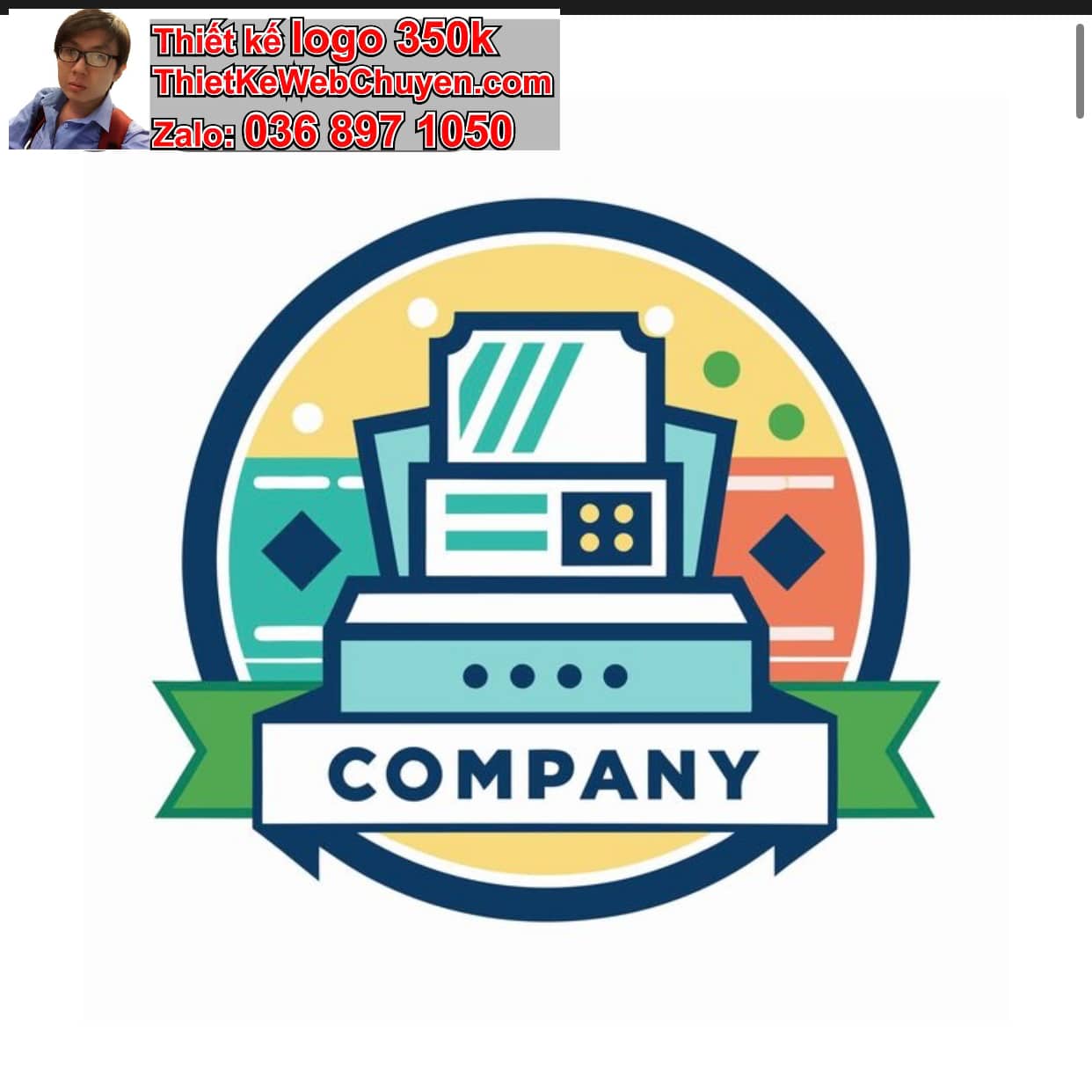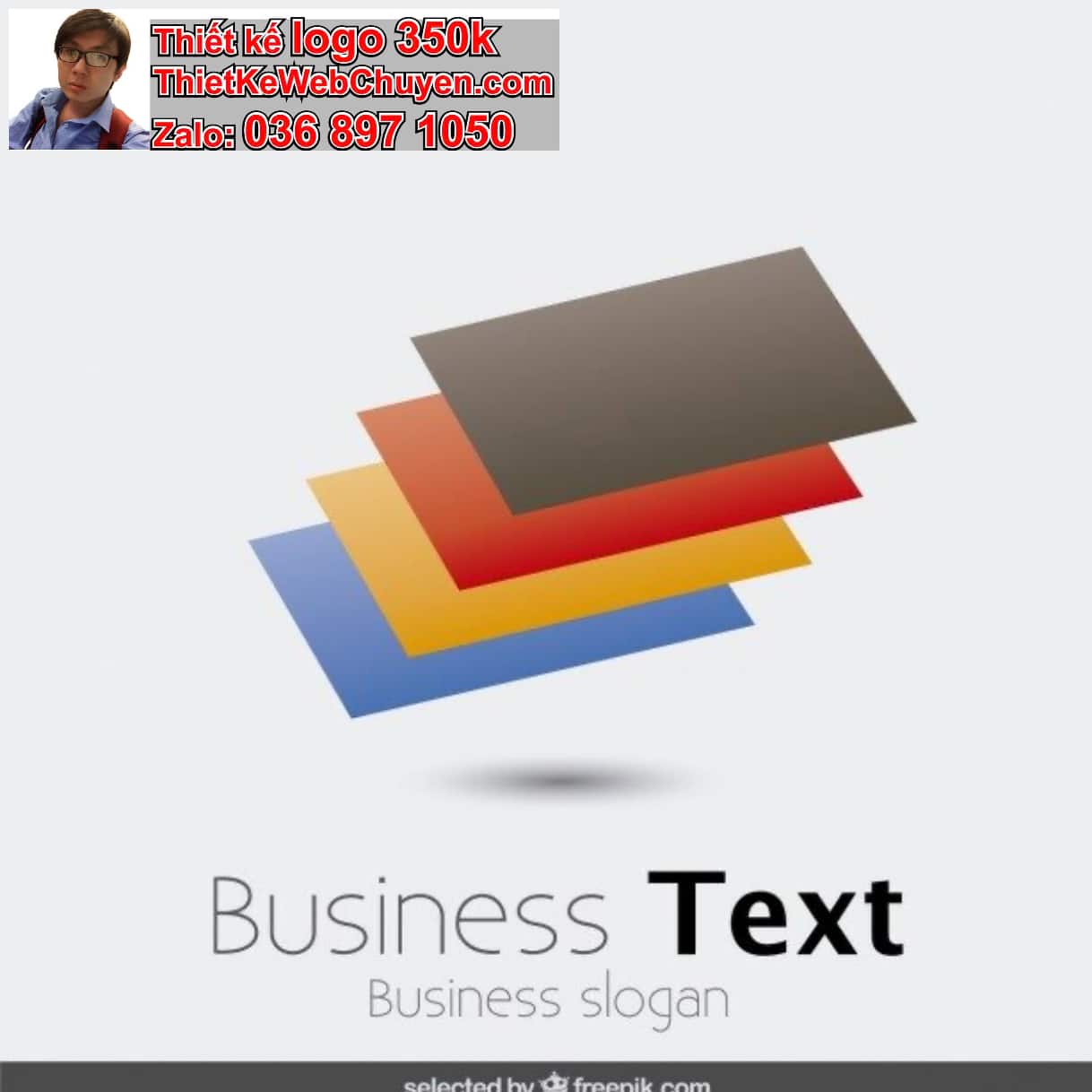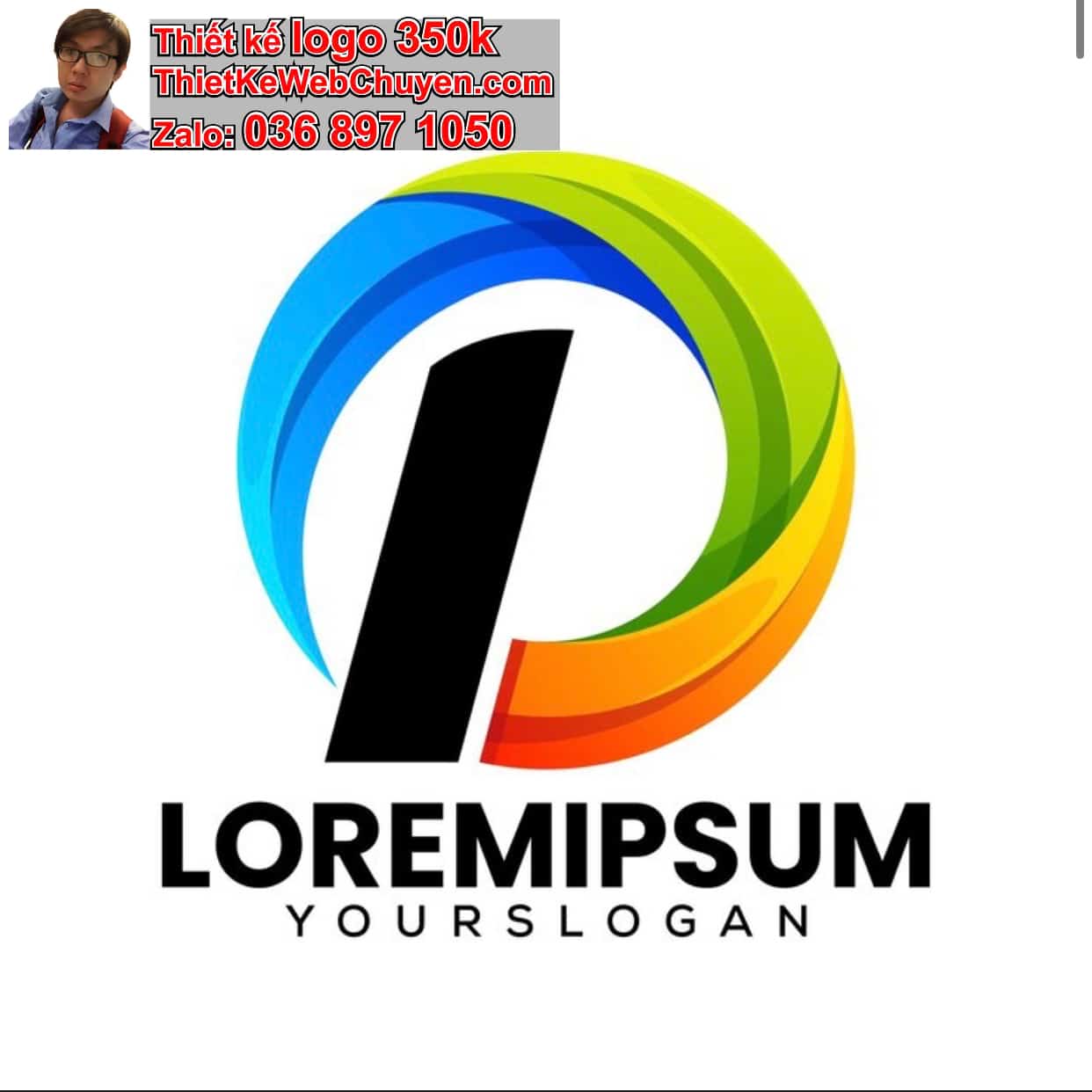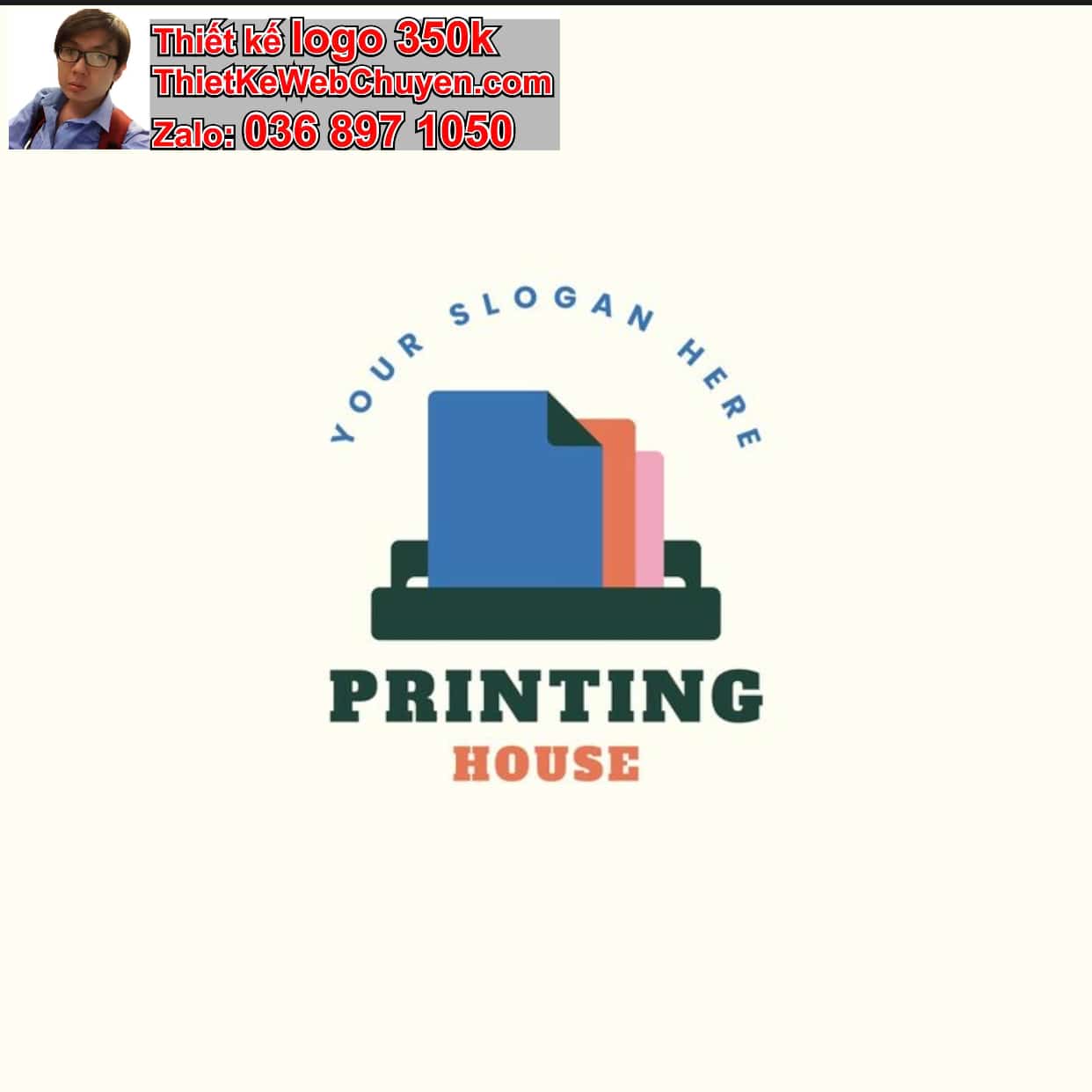
Bài viết này cung cấp hướng dẫn toàn diện về cách logo công ty chọn màu font biểu tượng khi ngân sách thấp, tập trung vào các nguyên tắc thiết kế hiệu quả và công cụ miễn phí. Bạn sẽ khám phá những bí quyết chọn màu sắc, font chữ và biểu tượng để tạo ra một nhận diện thương hiệu chuyên nghiệp mà không vượt quá hạn mức chi tiêu. Đảm bảo rằng dù với ngân sách hạn chế, bạn vẫn có thể sở hữu một logo công ty ấn tượng và thu hút.
Bạn đang khởi nghiệp hay điều hành một doanh nghiệp nhỏ với ngân sách hạn hẹp? Việc tạo dựng một thương hiệu mạnh mẽ bắt đầu từ một logo công ty ấn tượng, nhưng làm thế nào để có được một logo công ty chọn màu font biểu tượng khi ngân sách thấp mà vẫn chuyên nghiệp và hiệu quả? Đây là một thách thức chung mà nhiều chủ doanh nghiệp gặp phải.
Đừng lo lắng! Trong bài viết này, chúng ta sẽ cùng khám phá những chiến lược thông minh, các mẹo thực tế và nguồn tài nguyên hữu ích để giúp bạn tạo ra một logo công ty chọn màu font biểu tượng khi ngân sách thấp nhưng vẫn thể hiện được bản sắc và giá trị của thương hiệu. Mục tiêu của chúng ta là tối ưu hóa từng yếu tố – màu sắc, font chữ và biểu tượng – để đảm bảo rằng ngay cả với ngân sách hạn chế, bạn vẫn có thể sở hữu một logo đáng tự hào và thu hút khách hàng.
Tại sao việc chọn màu font biểu tượng cho logo công ty khi ngân sách thấp lại quan trọng?
Thiết kế logo không chỉ là việc tạo ra một hình ảnh đẹp mắt; đó là quá trình xây dựng bản sắc, gửi gắm thông điệp và tạo dấu ấn trong tâm trí khách hàng. Đặc biệt, khi bạn cần logo công ty chọn màu font biểu tượng khi ngân sách thấp, mỗi quyết định đều phải được cân nhắc kỹ lưỡng để đạt hiệu quả tối đa.
Logo công ty là gì và tầm quan trọng của nó?
Một logo công ty là bộ mặt của doanh nghiệp bạn. Nó là hình ảnh đầu tiên khách hàng nhìn thấy, là biểu tượng đại diện cho giá trị cốt lõi, sứ mệnh và tầm nhìn của công ty. Một logo hiệu quả có thể:
- Tạo ấn tượng đầu tiên mạnh mẽ: Một logo công ty độc đáo và dễ nhớ sẽ giúp bạn nổi bật giữa đám đông.
- Xây dựng sự nhận diện thương hiệu: Khi khách hàng nhìn thấy logo của bạn, họ ngay lập tức liên tưởng đến sản phẩm hoặc dịch vụ của bạn.
- Truyền tải thông điệp: Màu sắc, font chữ và biểu tượng trong logo có thể kể câu chuyện về doanh nghiệp của bạn.
- Tạo lòng tin và sự chuyên nghiệp: Một logo công ty được thiết kế tốt cho thấy sự nghiêm túc và chuyên nghiệp của bạn.
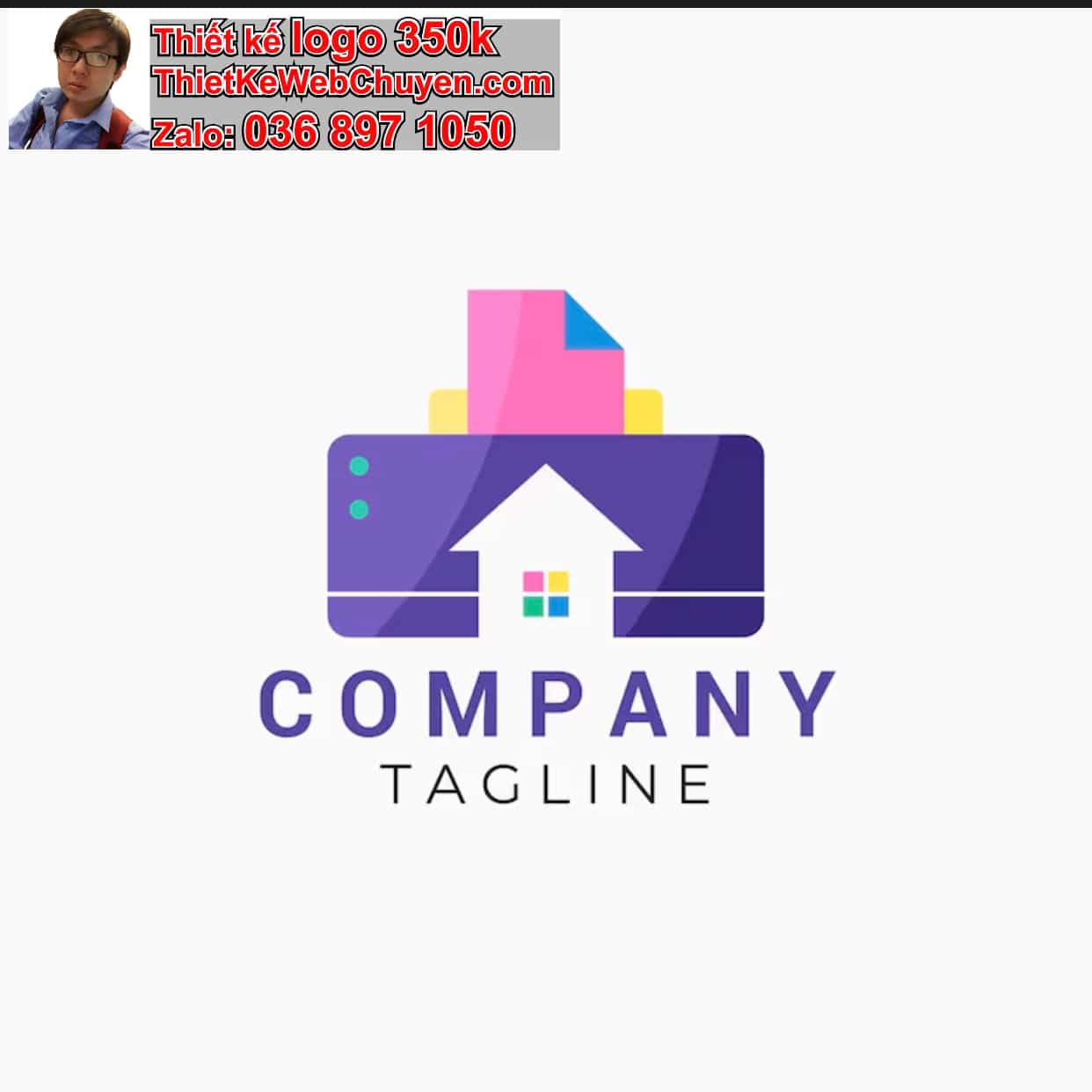
Những thách thức khi ngân sách thấp để tạo logo công ty chọn màu font biểu tượng?
Khi ngân sách thấp để tạo ra một logo công ty chọn màu font biểu tượng, bạn sẽ đối mặt với một số thách thức:
- Hạn chế thuê nhà thiết kế chuyên nghiệp: Chi phí thuê một agency hoặc nhà thiết kế dày dặn kinh nghiệm có thể vượt quá khả năng chi trả.
- Giới hạn về công cụ và tài nguyên cao cấp: Các phần mềm thiết kế chuyên nghiệp hoặc kho thư viện ảnh, icon bản quyền thường có phí.
- Nguy cơ tạo ra logo không chuyên nghiệp: Nếu không có kiến thức về thiết kế, bạn dễ mắc phải những sai lầm khiến logo trông nghiệp dư hoặc kém hiệu quả.
Tuy nhiên, với cách tiếp cận đúng đắn, bạn vẫn hoàn toàn có thể tạo ra một logo công ty chọn màu font biểu tượng khi ngân sách thấp nhưng vẫn đảm bảo chất lượng và tính chuyên nghiệp.
Làm thế nào để chọn màu sắc phù hợp cho logo công ty khi ngân sách thấp?
Màu sắc đóng vai trò cực kỳ quan trọng trong việc truyền tải cảm xúc và thông điệp của một logo công ty. Khi bạn cần một logo công ty chọn màu font biểu tượng khi ngân sách thấp, việc hiểu rõ tâm lý học màu sắc và cách sử dụng chúng một cách thông minh là chìa khóa.
Ý nghĩa tâm lý của màu sắc và cách áp dụng cho logo công ty
Mỗi màu sắc mang một ý nghĩa riêng và có thể tác động đến tâm trạng, cảm nhận của người nhìn. Hiểu rõ điều này giúp bạn có lựa chọn tối ưu cho logo công ty của mình:
- Đỏ: Năng lượng, đam mê, cấp bách, tình yêu, nguy hiểm. Thích hợp cho ngành thực phẩm, giải trí, thời trang.
- Xanh lam: Tin cậy, ổn định, bình yên, chuyên nghiệp, thông minh. Phổ biến trong tài chính, công nghệ, y tế.
- Xanh lá: Thiên nhiên, tăng trưởng, sức khỏe, sự tươi mới, tiền bạc. Thích hợp cho ngành môi trường, nông nghiệp, thực phẩm hữu cơ.
- Vàng: Vui vẻ, lạc quan, năng lượng, sáng tạo. Thường dùng trong du lịch, giáo dục, sản phẩm trẻ em.
- Tím: Sang trọng, sáng tạo, bí ẩn, trí tuệ. Phù hợp với sản phẩm cao cấp, làm đẹp, nghệ thuật.